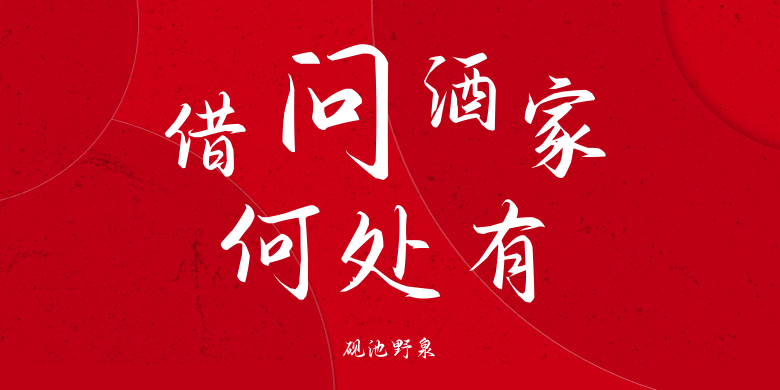
砚池野泉
砚池野泉,这款字体结构工整、笔画清晰,兼顾美观与易读性,适用于标题、正文、海报、包装、LOGO 等多种场景。字形优雅稳定,风格百搭耐看,适配日常排版与创意设计,让文字呈现更舒适、更具质感。砚池野泉一笔一画,皆是细节,以均衡的比例、流畅的线条打造舒适视觉体验,字形端正大气,风格简约现代。无论是商业设计、品牌宣传还是日常排版,都能轻松驾驭,让文字更有格调与力量。砚池野泉字体下载。